45 font chữ 8/3 Việt hóa đẹp, được ưa chuộng nhất 2026
Font chữ 8/3 là một phần không thể thiếu trong các thiết kế dành riêng cho ngày Quốc tế Phụ nữ. Để tôn vinh vẻ đẹp và sự đóng góp của phái đẹp, việc lựa chọn font chữ chúc mừng 8/3 phù hợp là vô cùng quan trọng. Bài viết này sẽ giới thiệu đến bạn 45+ mẫu font chữ 8/3 Việt hóa đẹp, được ưa chuộng nhất 2026. Xem ngay nhé!
Việc chọn font chữ 8/3 phù hợp cho thiết kế, giúp tôn vinh vẻ đẹp của phái nữ. Dưới đây là những font chữ 8/3 đẹp, được ưa chuộng nhất trong năm 2026.
Apricots là một font chữ viết tay mang phong cách thanh lịch, nhẹ nhàng. Phù hợp với các thiết kế thiệp chúc mừng, banner hoặc bài đăng mạng xã hội nhân ngày 8/3. Font này có nét chữ mềm mại, tự nhiên, tạo cảm giác gần gũi và ấm áp.
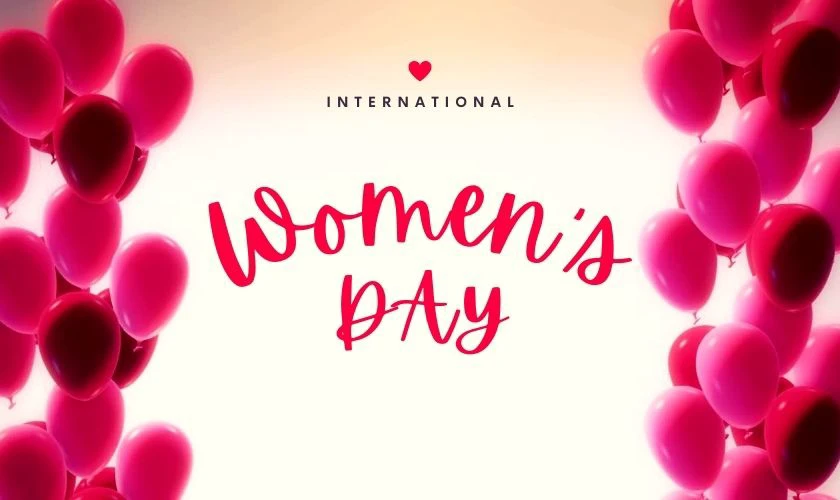
Một điểm đặc biệt của Apricots là sự kết hợp hài hòa giữa các ký tự. Giúp người dùng dễ dàng tạo ra những thiết kế mang tính cá nhân hóa. Font chữ này không chỉ thích hợp cho các mẫu thiệp mà còn lý tưởng cho typography trên hình ảnh.
Great Vibes là một trong những font chữ 8/3 phổ biến, được yêu thích nhờ vào nét chữ uyển chuyển, bay bổng. Đây là lựa chọn tuyệt vời cho các thiệp chúc mừng, lời nhắn yêu thương nhân dịp 8/3.
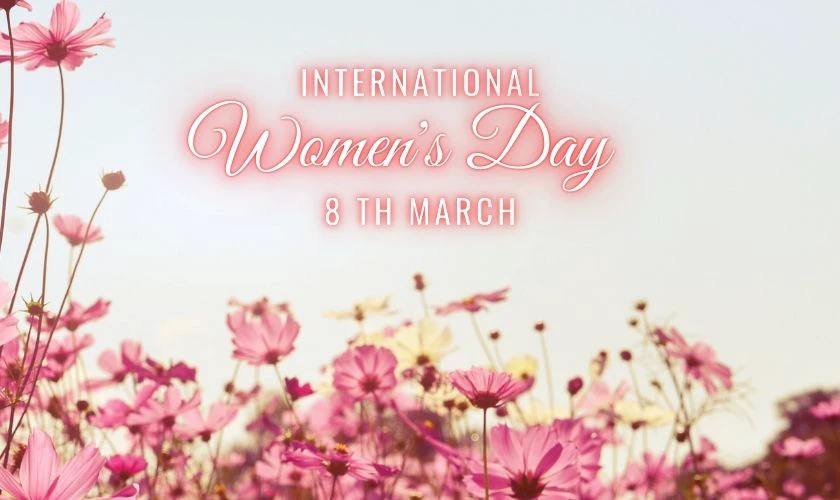
Sở hữu độ cong mềm mại và độ dày vừa phải, Great Vibes giúp các thiết kế trở nên cuốn hút mà không quá rối mắt. Nếu bạn đang tìm kiếm một font chữ có thể truyền tải sự tinh tế, Great Vibes chắc chắn là một gợi ý hoàn hảo.
Amsterdam One là font chữ chúc mừng 8/3 mang phong cách viết tay cổ điển nhưng vẫn giữ được nét hiện đại. Nét chữ có sự chuyển đổi linh hoạt giữa thanh mảnh và dày dặn, giúp tạo điểm nhấn cho nội dung.
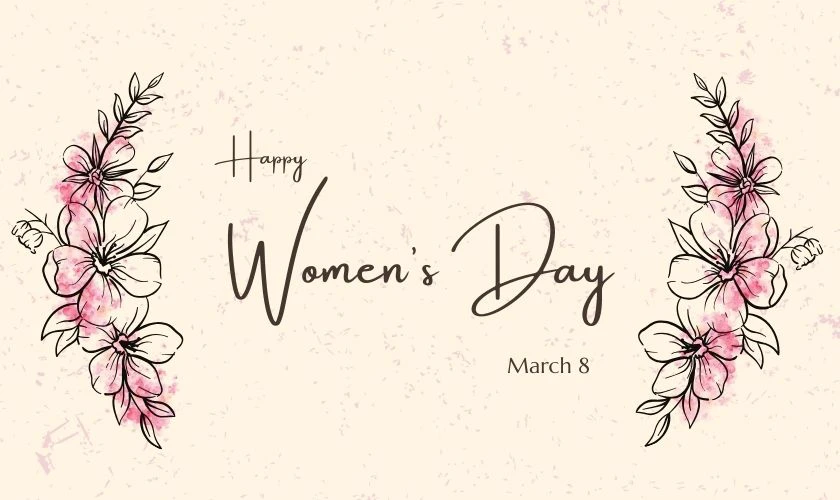
Font Amsterdam One đặc biệt thích hợp cho các ấn phẩm mang phong cách nghệ thuật hoặc vintage. Với các đường nét mềm mại nhưng vẫn rõ ràng, nó giúp tôn lên sự thanh lịch và trang nhã trong từng thiết kế.
The Seasons là một font chữ 8/3 serif mang hơi hướng sang trọng, tinh tế. Đây là một lựa chọn tuyệt vời nếu bạn muốn tạo ra những thiết kế thanh lịch nhưng vẫn có sự mạnh mẽ.
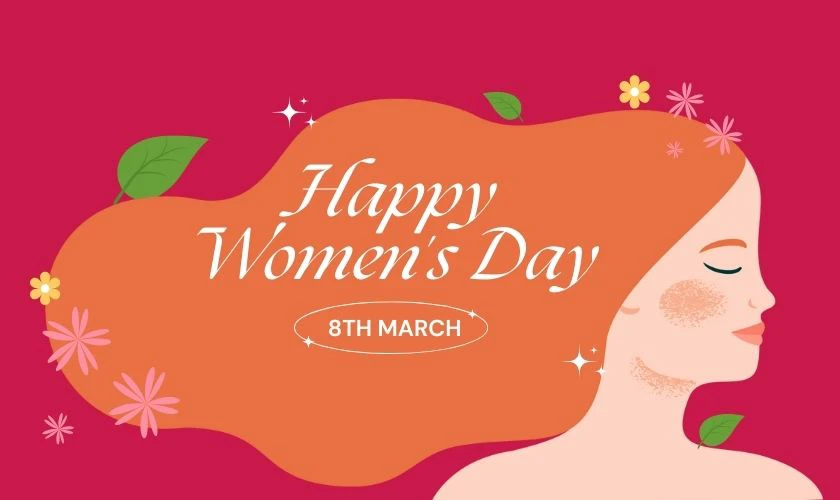
Font chữ này có các ký tự với đường nét sắc sảo, giúp văn bản trở nên nổi bật và dễ đọc hơn. Sự kết hợp giữa phong cách cổ điển và hiện đại của The Seasons sẽ mang đến vẻ đẹp trang nhã, chuyên nghiệp.
Merriweather là font serif có độ dày vừa phải, mang đến cảm giác gần gũi nhưng vẫn đảm bảo tính thẩm mỹ cao. Với thiết kế thanh lịch, Merriweather phù hợp cho các bài viết chúc mừng, typography trên hình ảnh và thiệp 8/3.
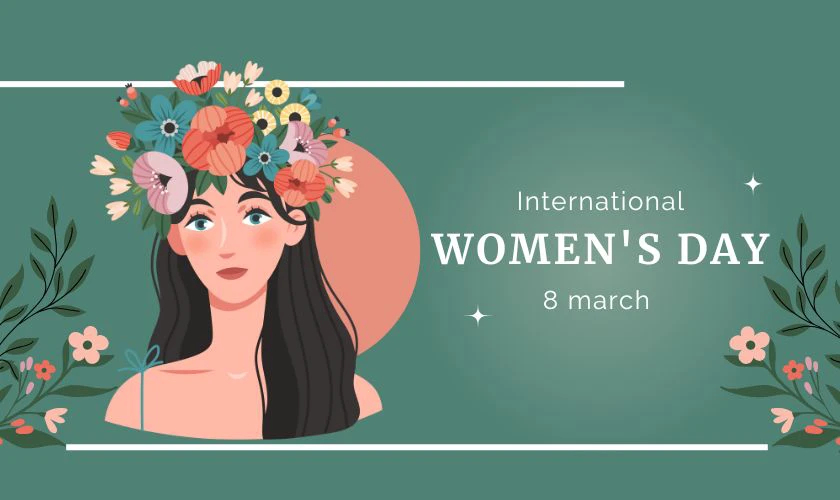
Điểm nổi bật của Merriweather là khả năng hiển thị rõ ràng trên cả nền sáng và nền tối. Giúp người thiết kế dễ dàng áp dụng trong nhiều bối cảnh khác nhau.
Nếu bạn đang tìm kiếm các font chữ 8/3 đẹp thì font chữ Việt hóa dưới đây sẽ là lựa chọn tuyệt vời.
SVN-The Carpenter là font chữ 8/3 mang phong cách viết tay thanh lịch, mềm mại. Các đường nét uốn lượn tạo nên cảm giác nghệ thuật, phù hợp để làm typography trên ấn phẩm dành riêng cho ngày 8/3.
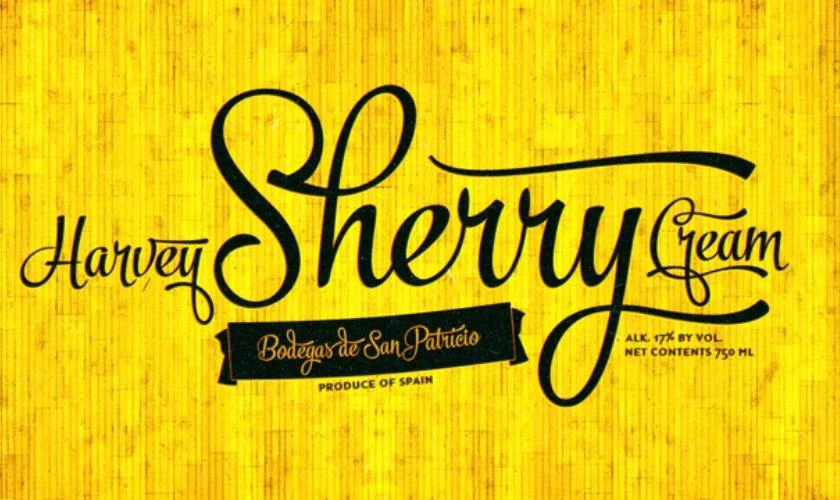
Với việc hỗ trợ đầy đủ tiếng Việt, SVN-The Carpenter giúp bạn có thể sáng tạo mà không gặp phải vấn đề lỗi font. Font chữ này rất lý tưởng cho những thiết kế có phong cách cổ điển nhưng vẫn giữ được nét hiện đại.
SVN-Silver là font chữ chúc mừng 8/3 script có phong cách nhẹ nhàng, tối giản nhưng đầy tinh tế. Font này phù hợp cho các thiết kế cần sự mềm mại, bay bổng như thiệp chúc mừng hoặc các bài đăng trên mạng xã hội nhân dịp 8/3.
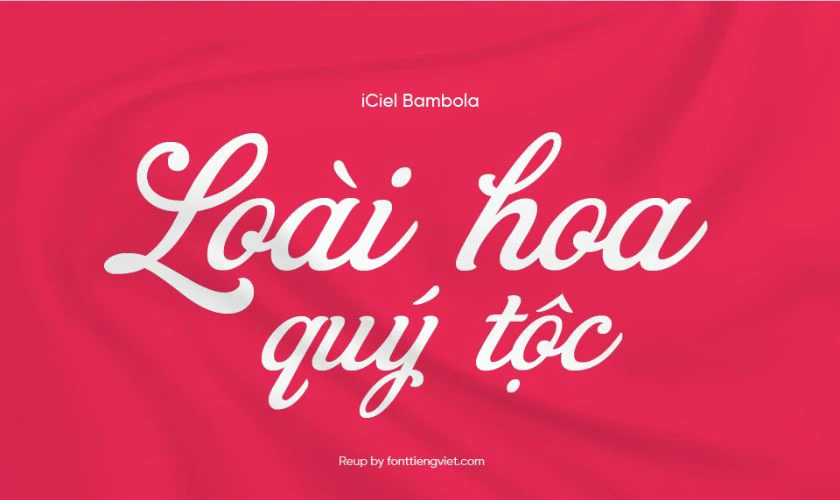
Với những đường nét thanh thoát, SVN-Silver mang đến vẻ đẹp trang nhã, nữ tính. Điểm cộng lớn của font chữ này là nó có thể kết hợp dễ dàng với nhiều kiểu chữ khác để tạo nên một tổng thể hài hòa.
UVF Slim Tony là một font chữ 8/3 mang phong cách hiện đại với các đường nét mảnh mai nhưng dứt khoát. Font chữ này rất phù hợp cho những ai yêu thích sự tối giản nhưng vẫn muốn tạo điểm nhấn.
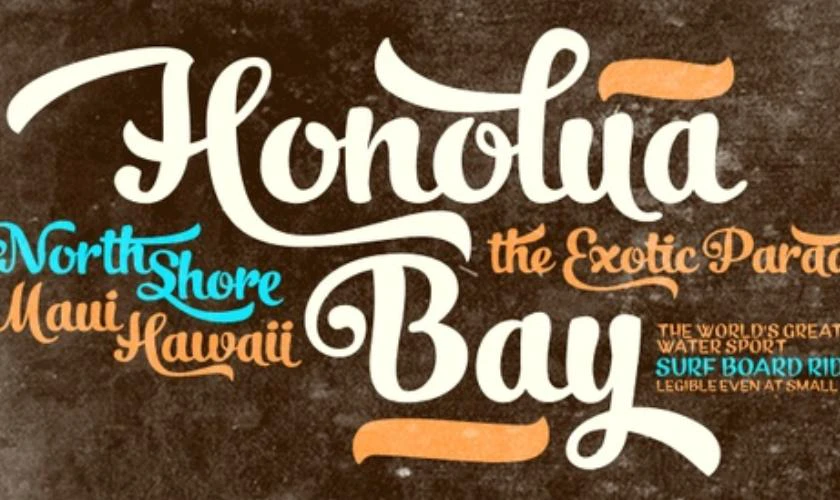
Một ưu điểm lớn của UVF Slim Tony là tính ứng dụng cao, có thể sử dụng trong nhiều loại thiết kế khác nhau. Cụ thể như banner, thiệp chúc mừng hoặc typography trên hình ảnh. Nhờ vào đường nét thanh mảnh và cấu trúc cân đối, font chữ này giúp nội dung trở nên cuốn hút hơn.
SVN-Amethyst mang đến cảm giác huyền bí và sang trọng nhờ các đường nét uốn lượn mềm mại. Font chữ 8/3 này được thiết kế với độ dày vừa phải, giúp dễ dàng tạo ra những dòng chữ ấn tượng.
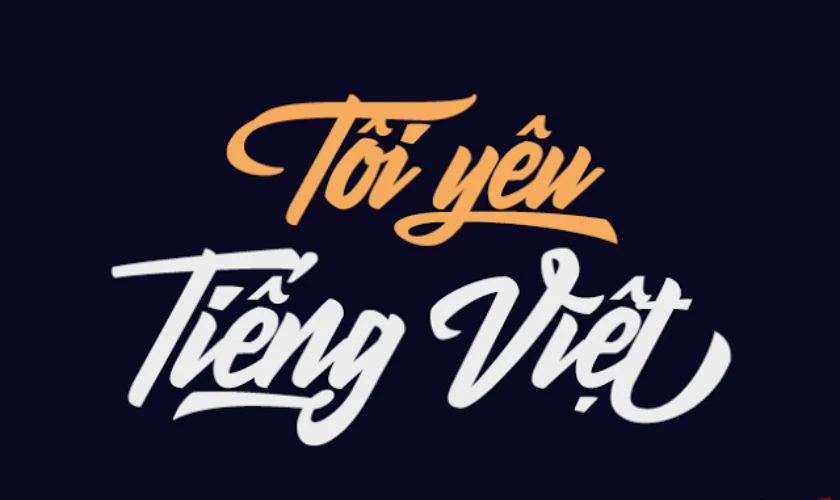
Ngoài yếu tố thẩm mỹ, SVN-Amethyst còn có khả năng hiển thị tốt trên cả nền sáng và nền tối. Đây là một lựa chọn lý tưởng nếu bạn muốn mang đến một nét cuốn hút đặc biệt cho thiết kế của mình.
SVN Zara Elyse là một font chữ 8/3 mang phong cách hiện đại, tinh tế. Font chữ này có sự cân bằng hoàn hảo giữa các nét thanh và nét đậm.
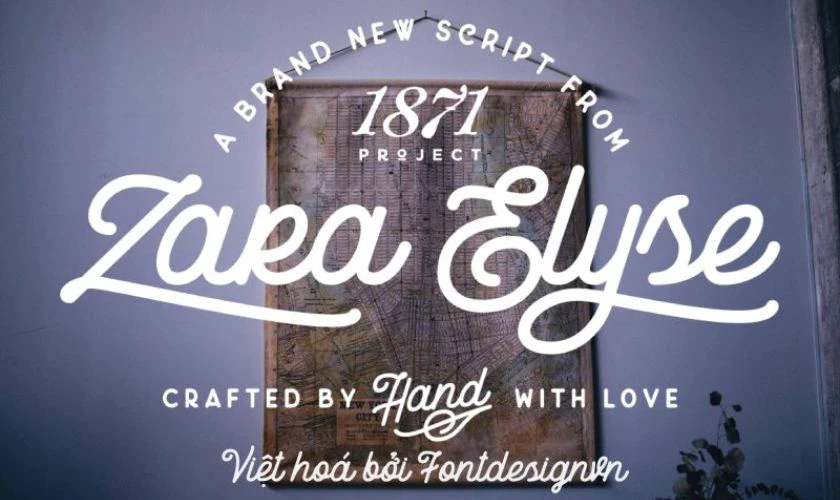
Sở hữu những đường nét nhẹ nhàng nhưng không kém phần phá cách. SVN Zara Elyse thích hợp cho các thiết kế thiệp chúc mừng, banner hoặc typography nghệ thuật. Nếu bạn đang tìm kiếm một font chữ vừa nữ tính, vừa thời thượng thì đây là một lựa chọn đáng cân nhắc.